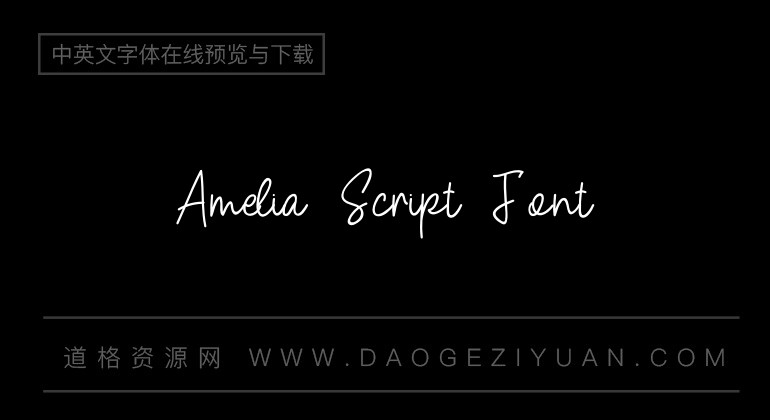
Amelia Script Font 是一种优美的手写字体,它的设计灵感来自于自然风景和手写书法艺术。该字体具有流畅的曲线和优美的笔画,可以为设计师和艺术家们提供出色的创意工具。 Amelia Script Font 适用于各种设计项目,包括品牌标志、包装设计、海报、名片、书籍封面和手写风格的广告。 它具有一个完整的字符集,包括大写字母、小写字母、数字和标点符号,使得它可以满足各种设计需求。 此外,Amelia Script Font 也具有多语言支持,包括西班牙语、法语、德语等语言,这使得它成为一个非常全面的字体选择。如果你正在寻找一种优美的手写字体来增强你的设计作品,Amelia Script Font 可以成为一个不错的选择。内容介绍
Amelia Script Font是一款非常不错的手写艺术字体,具有很好的视觉感,适合于文化类的宣传设计、商业类品牌的广告和产品包装设计以及个性化文字排版等较多场景。